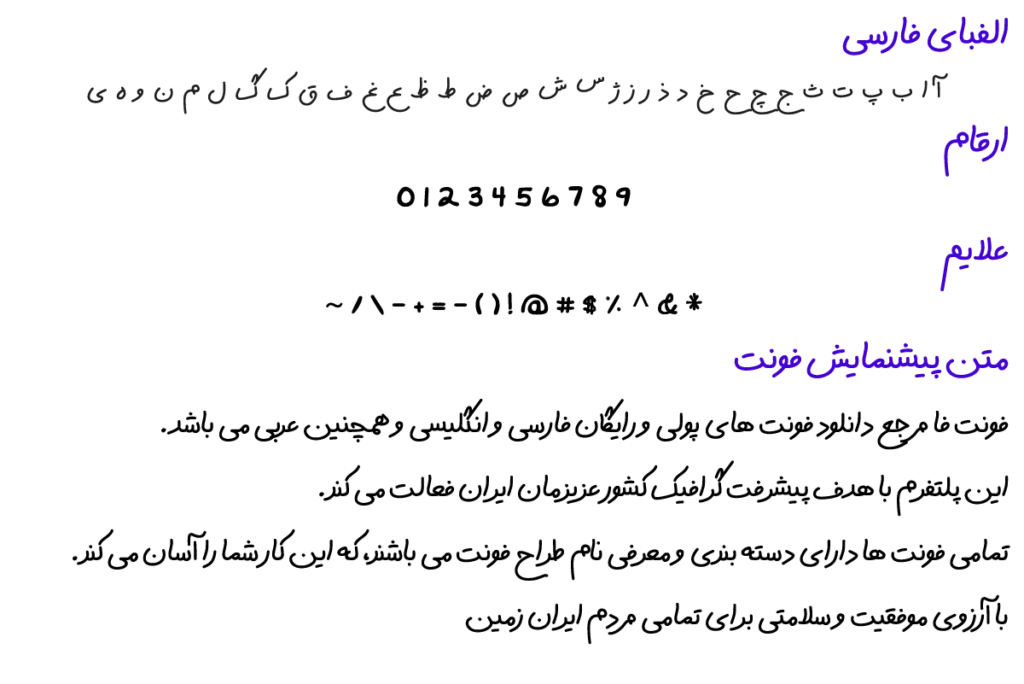
فونت فارسی دیجی هیلان – Digi Hilan
طراح فونت: مهدی برقگیر نوع فونت: فونت دست نویس
پیشنمایش فونت دیجی هیلان
توضیحات و معرفی فونت دیجی هیلان
فونت فارسی دیجی هیلان ( Digi Hilan ) از مجموعه فونت های آزاد می باشد، و نیز نوع فونت دست نویس می باشد.
فونت خوشگل مربوط توسط مهدی برقگیر در سال 1399 طراحی و ساخته شده است.
این تایپ فیس گزینه ای مناسب برای طراحی عکس نوشته، جملات عاشقانه و استوری های عاشقانه است.
به دلیل فرم و حالت خاص حروف، میتوانید به راحتی از آن در متن های طولانی نیز استفاده کنید.
تصویر زیر دموی فونت با شعر زیبای وطنم می باشد.